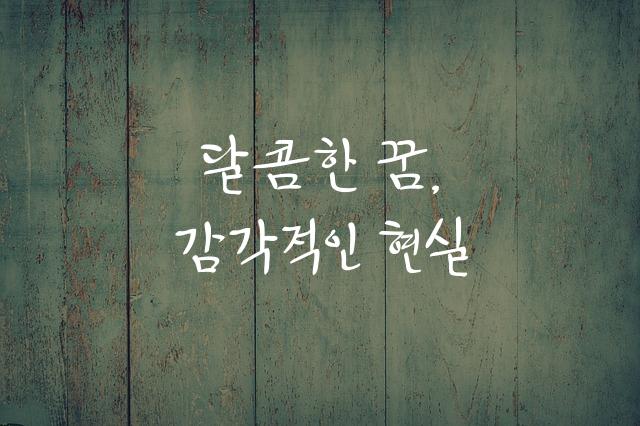
한용운체는 GS칼텍스에서 제작한 캘리그라피 스타일의 폰트로, 삐뚤빼뚤한 어른 손글씨의 감성을 담고 있습니다. 이 폰트는 따뜻하고 인간적인 느낌을 전달하며, 감성적인 디자인에 적합합니다.
한용운체은(는)
손글씨, 펜/붓터치, 감성적인, 부드러움 계열의 생김새를 가지고 있으며
출판 디자인, 출판물 제목, 일기/편지 등에서 자주 활용되며, 효과적인 메시지 전달에 적합합니다.
이 폰트는 출판/미디어, 문화/예술, 공공/정부 분야에 잘 어울리며,
감성적인, 전통적, 클래식한 느낌을 담고 있는 것이 특징입니다.